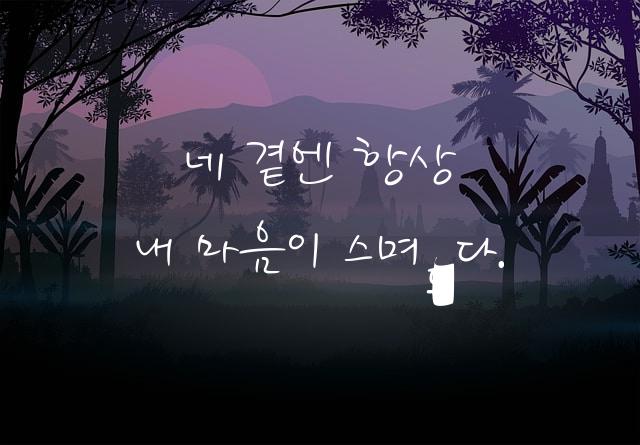
정림사지는 부여군 지역공동체 활성화 재단에서 제작한 전통적 감성의 바탕체 폰트입니다. 이 폰트는 한글의 아름다움을 현대적인 감각으로 재해석하여, 따뜻하고 친근한 느낌을 전달합니다.
정림사지은(는)
바탕 스타일 계열의 생김새를 가지고 있으며
출판 디자인, 제품 포장, 출판물 제목 등에서 자주 활용되며, 효과적인 메시지 전달에 적합합니다.
이 폰트는 출판/미디어, 문화/예술, 이벤트/웨딩 분야에 잘 어울리며,
전통적, 고급스러운, 클래식한 느낌을 담고 있는 것이 특징입니다.